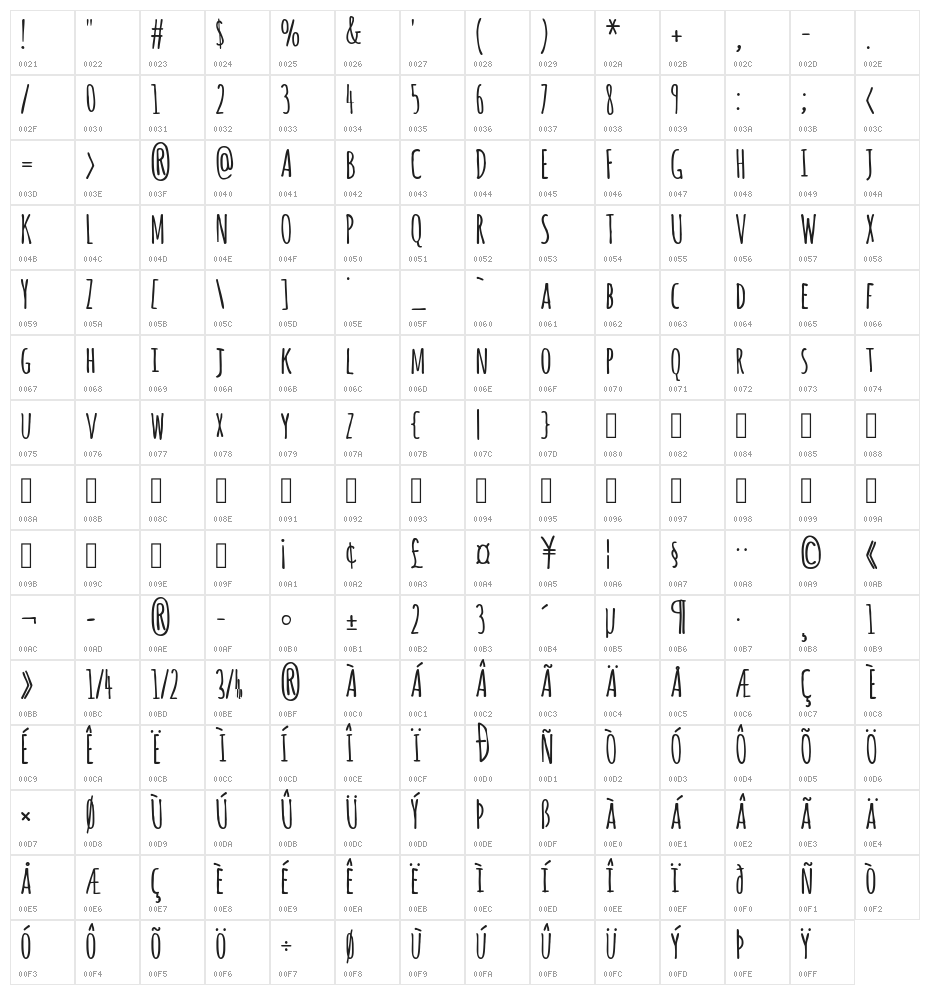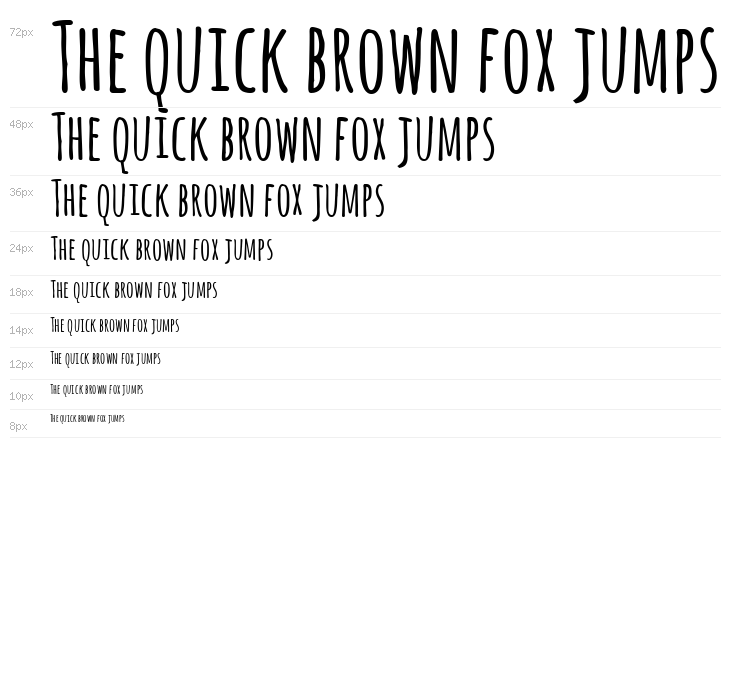
Amatic Bold Font
| العرض | Condensed |
| النمط العام | Casual, Playful |
| حالة الاستخدام | Headlines, Posters, Invitations |
| مشاريع مقترحة | Ideal for creative projects such as posters, invitations, and branding materials where a unique, informal touch is desired. |